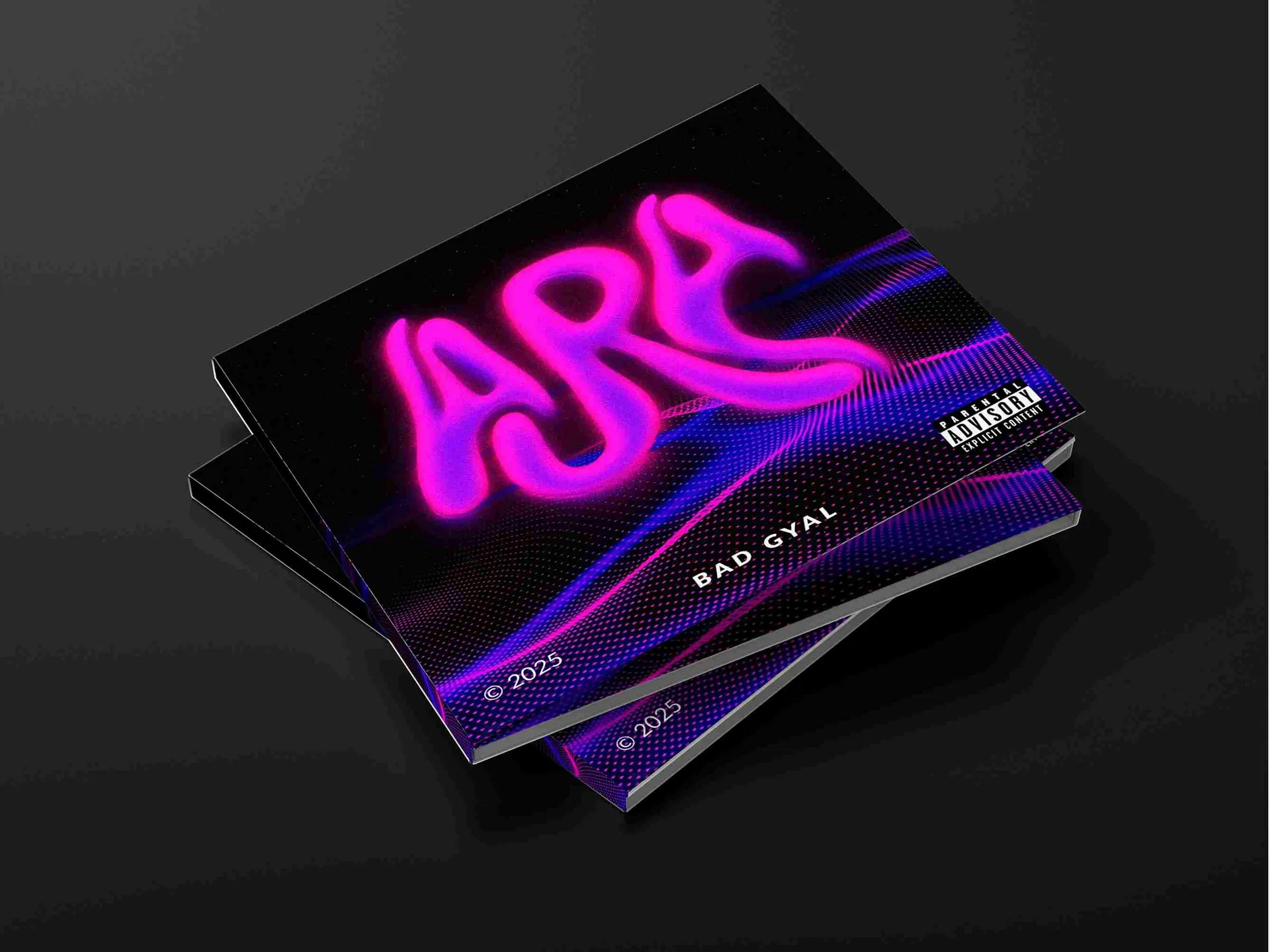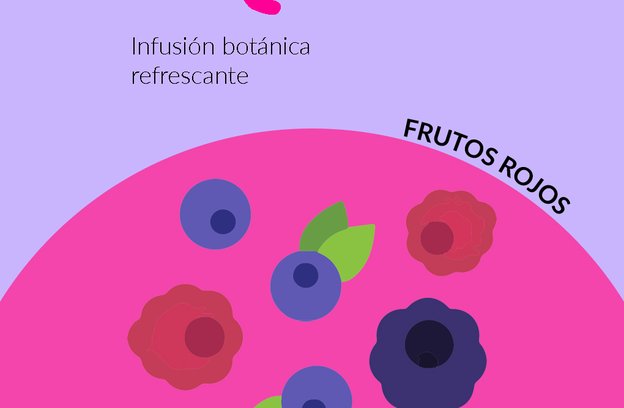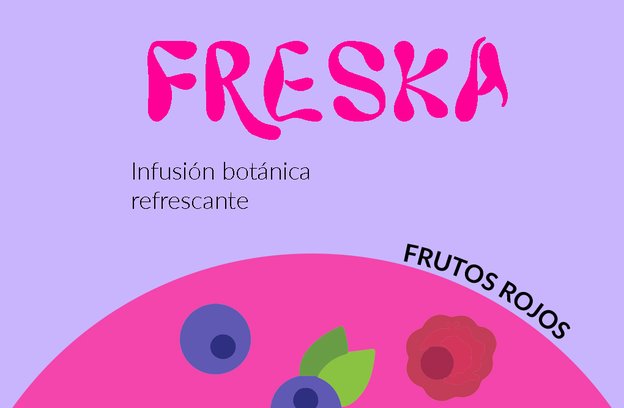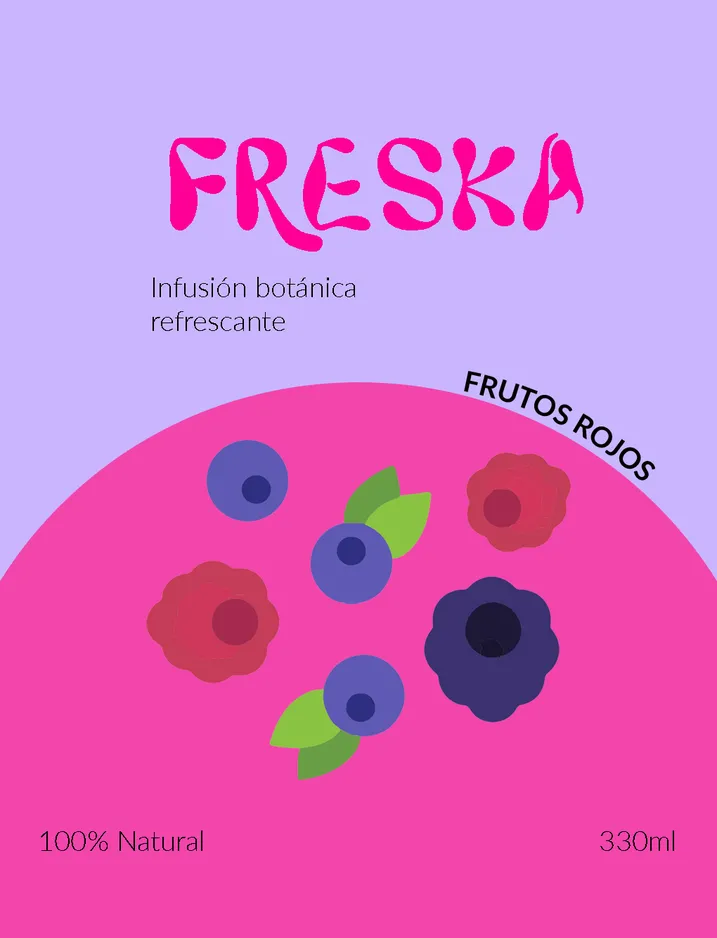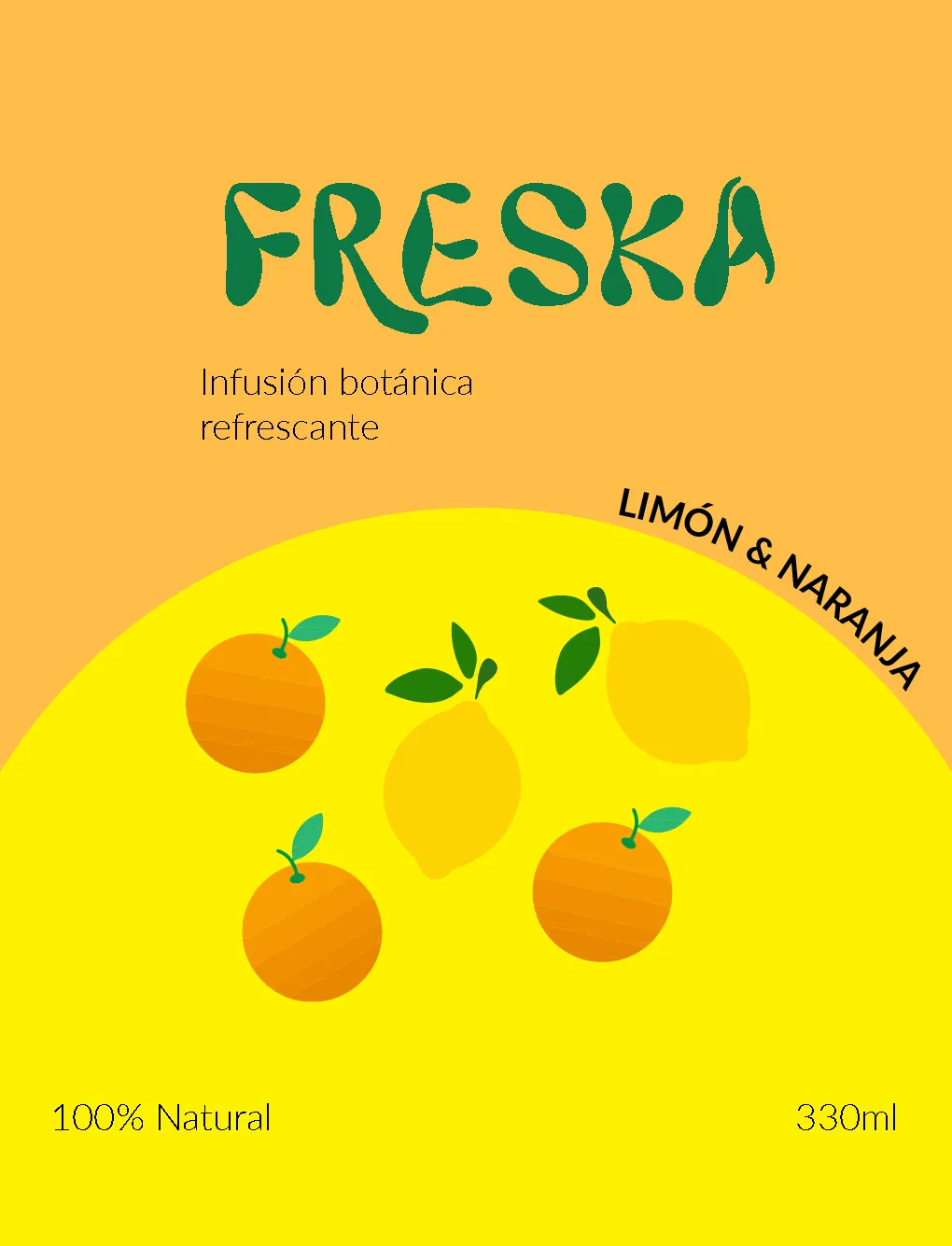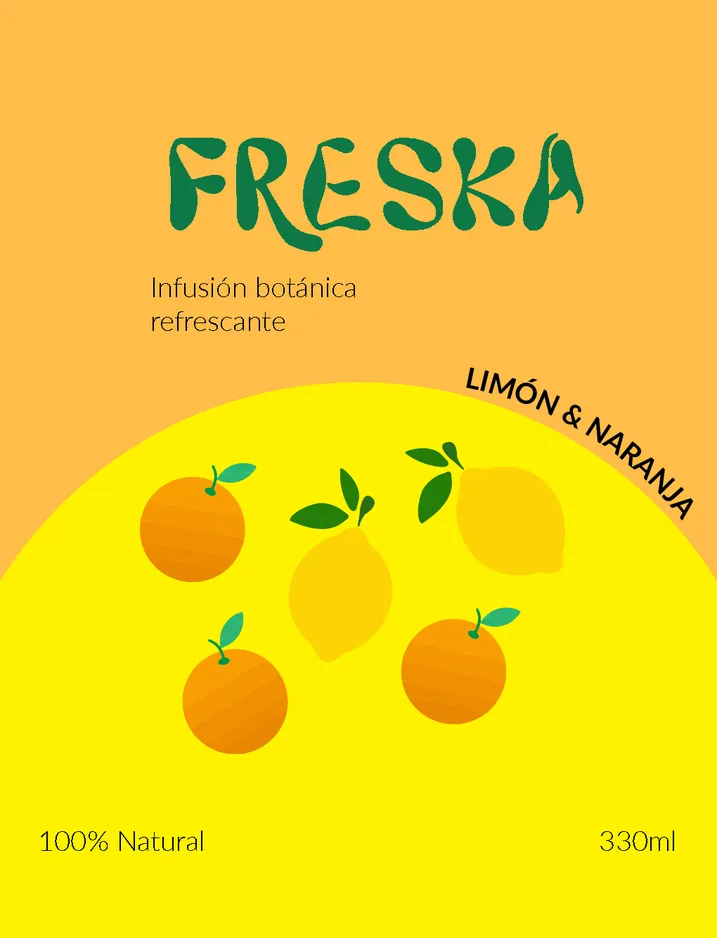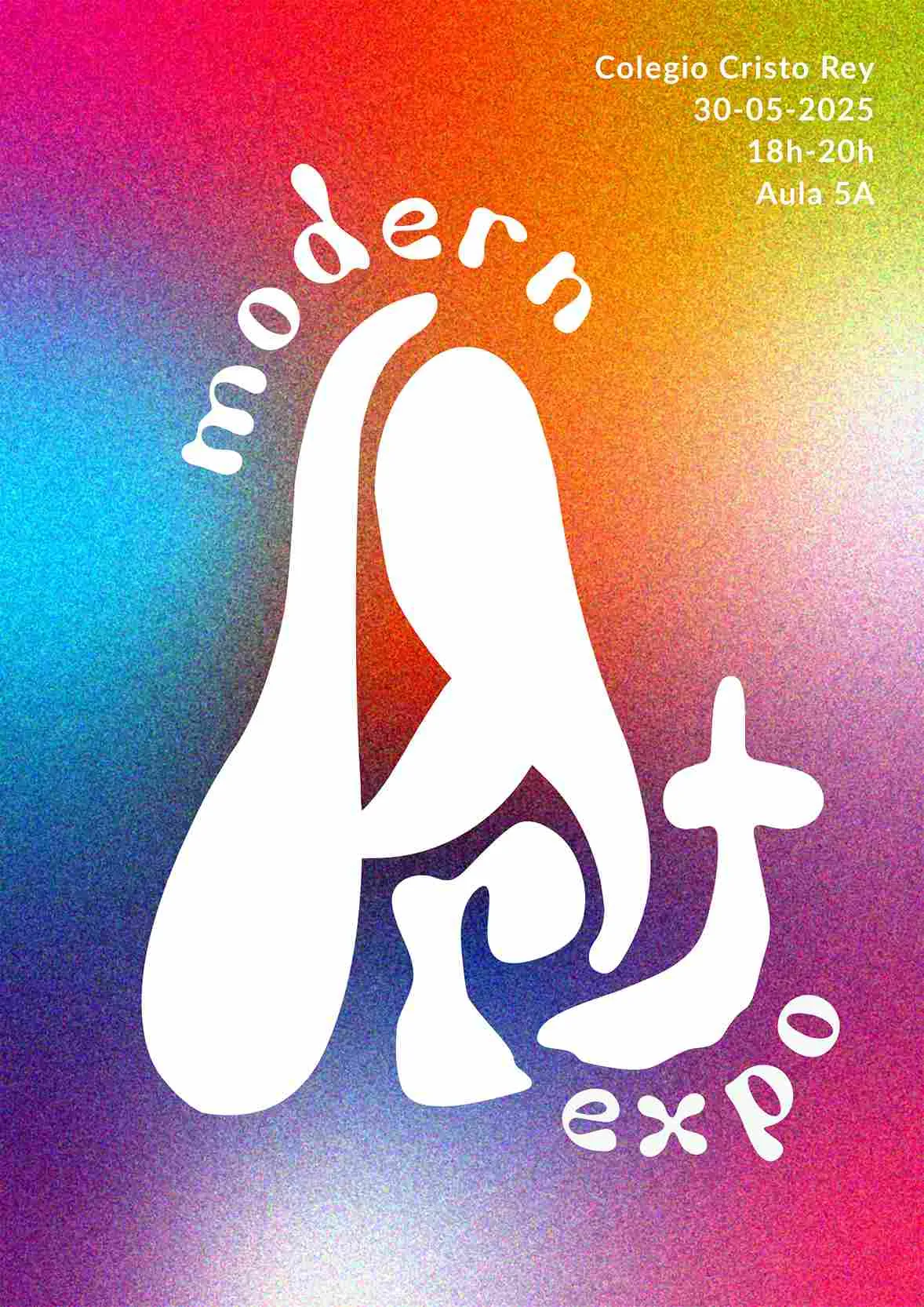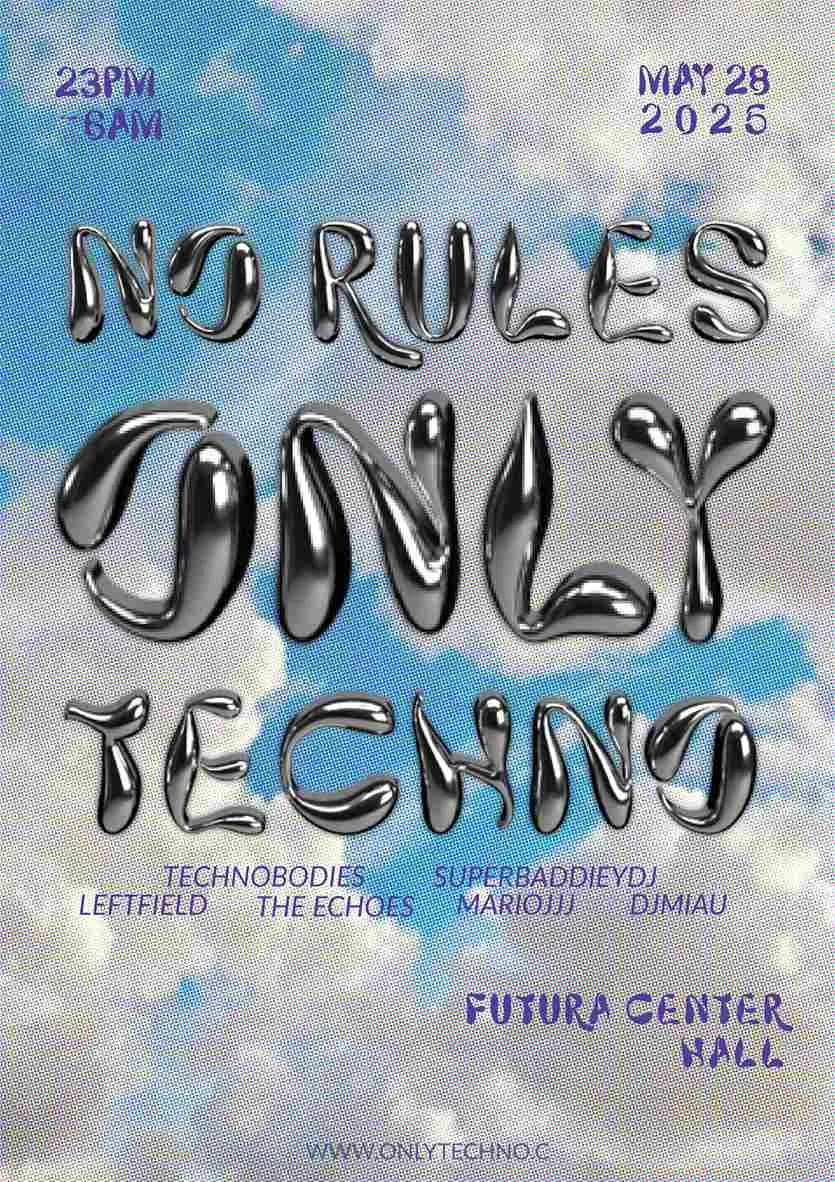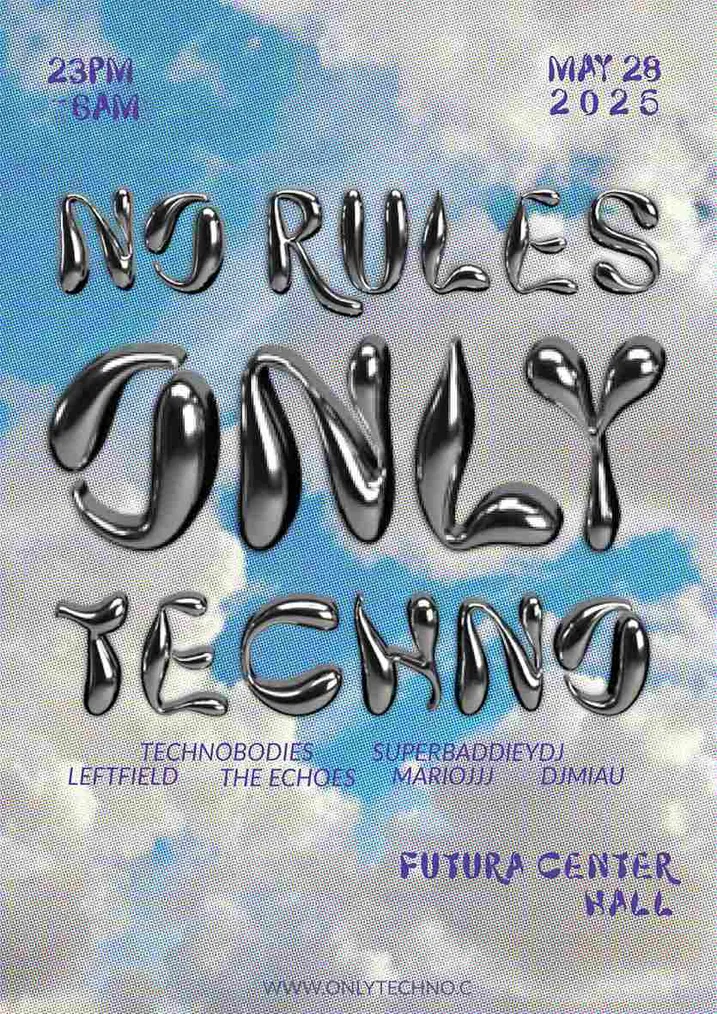
Como parte de una práctica de diseño tipográfico centrada en el concepto de utopía, desarrollamos una tipografía display que busca representar visualmente una sociedad ideal desde una perspectiva natural, fluida y en constante transformación. Inspirándonos en la obra Utopía de Tomás Moro y en nuestras propias interpretaciones contemporáneas, creamos una propuesta que combina lo humano, lo orgánico y lo futurista.